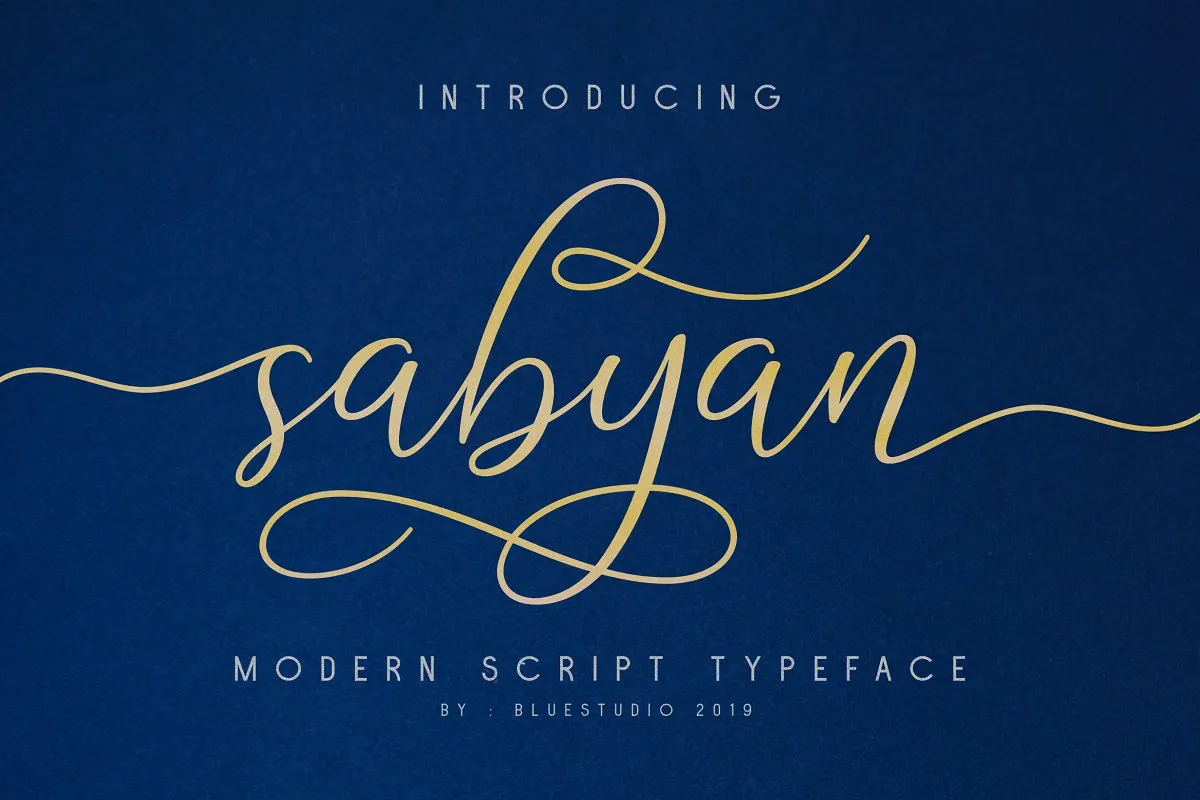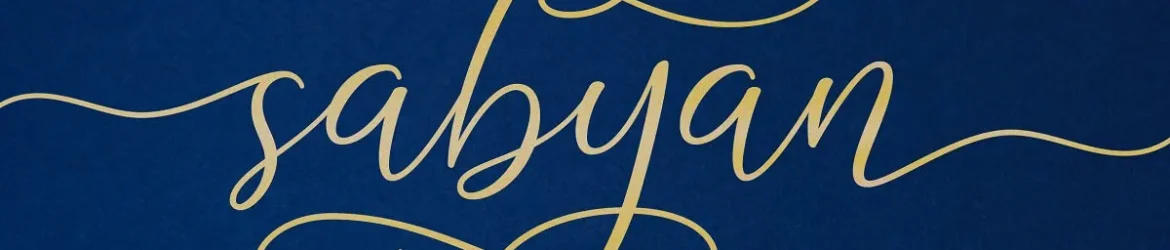
A Sabyan Script Font é uma moderna tipografia de calligrafia criada por zziplex para aqueles que buscam uma alternativa perfeita para suas necessidades de design. Introduzida como um tipo de escrita manual fresco e elaborado, esta fonte está perfeitamente equipada para atender a uma ampla gama de projetos gráficos. Se você procura uma fonte que se assemelhe à sua própria escrita manuscrita, Sabyan Script é uma excelente escolha. Ideal tanto para criações de logomarca e identidade visual como para capas, outdoors, revistas e cartazes, a Sabyan Script Font oferece uma aparência moderna e limpa. Seu design se destaca por sua facilidade em adaptar-se a diversos usos dentro do mundo da comunicação visual, tornando-a um recurso valioso tanto para profissionais quanto para amadores que desejam incorporar um toque especial em seus projetos. Seja você criando cartões de aniversário, convites para casamentos ou até mesmo frases inspiradoras e emocionantes em suas produções digitais, a Sabyan Script Font oferecerá uma experiência de usabilidade única que garantirá um resultado profissional. Esta fonte é perfeita para aqueles buscando transpor seu estilo pessoal para o mundo digital através do design gráfico.